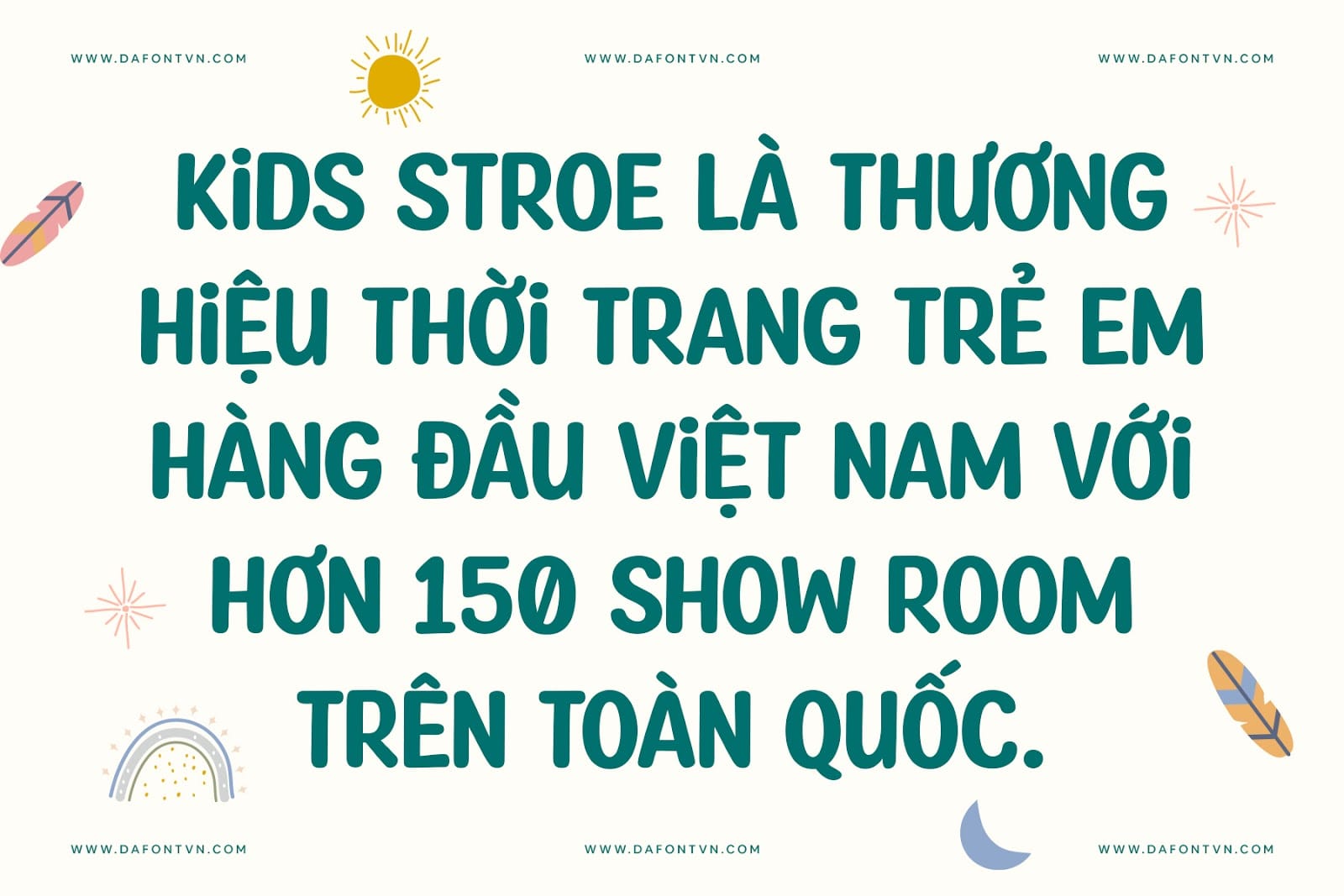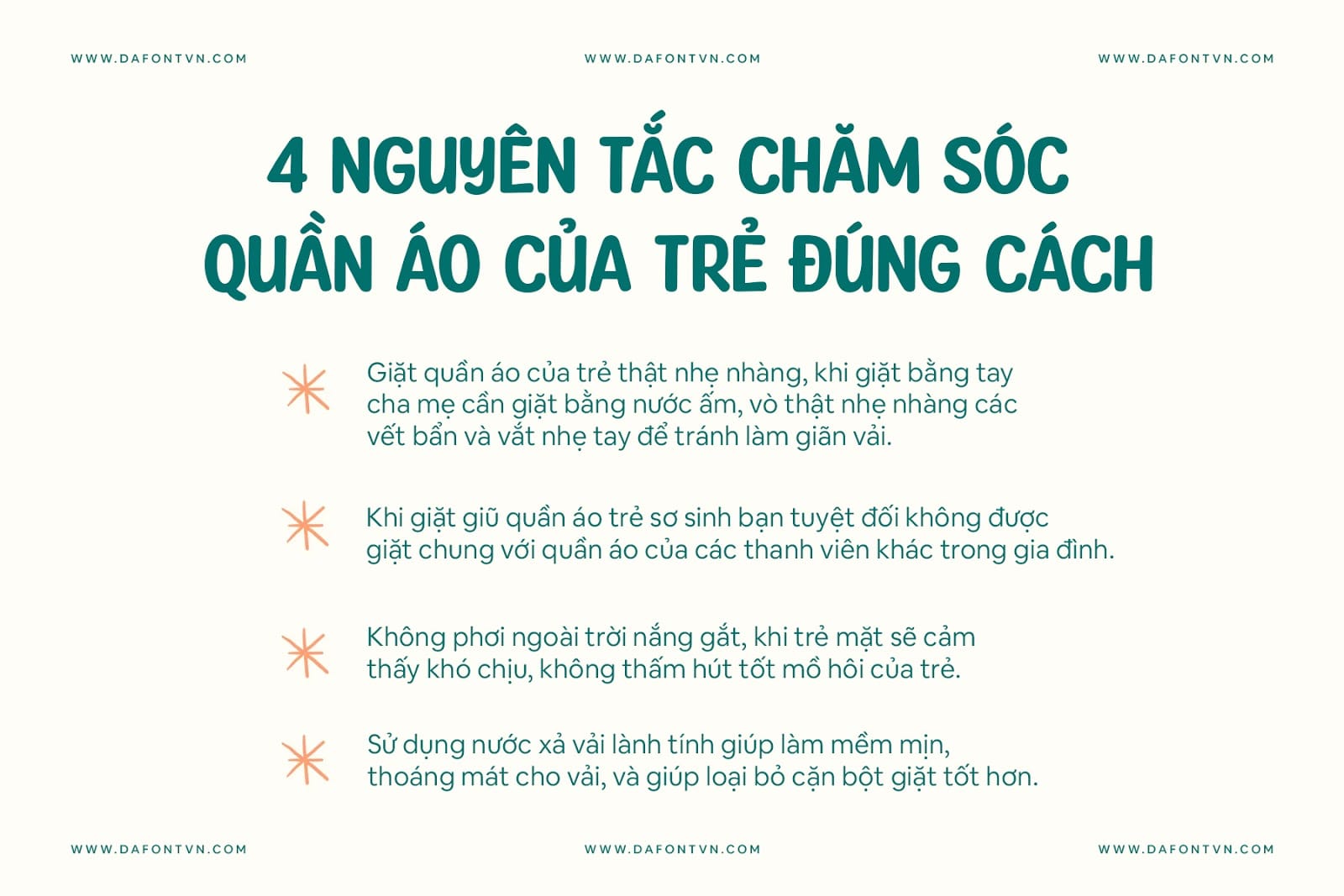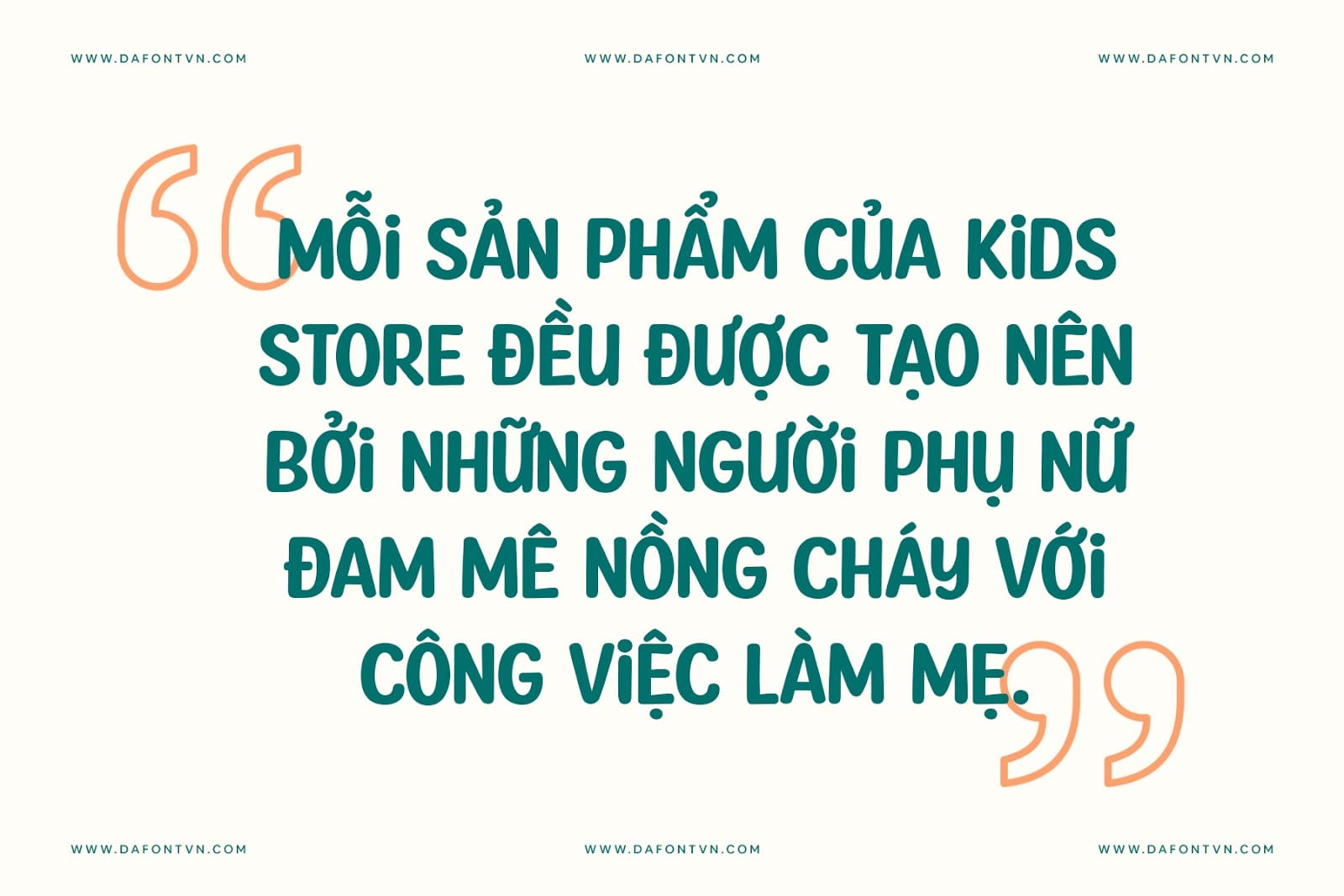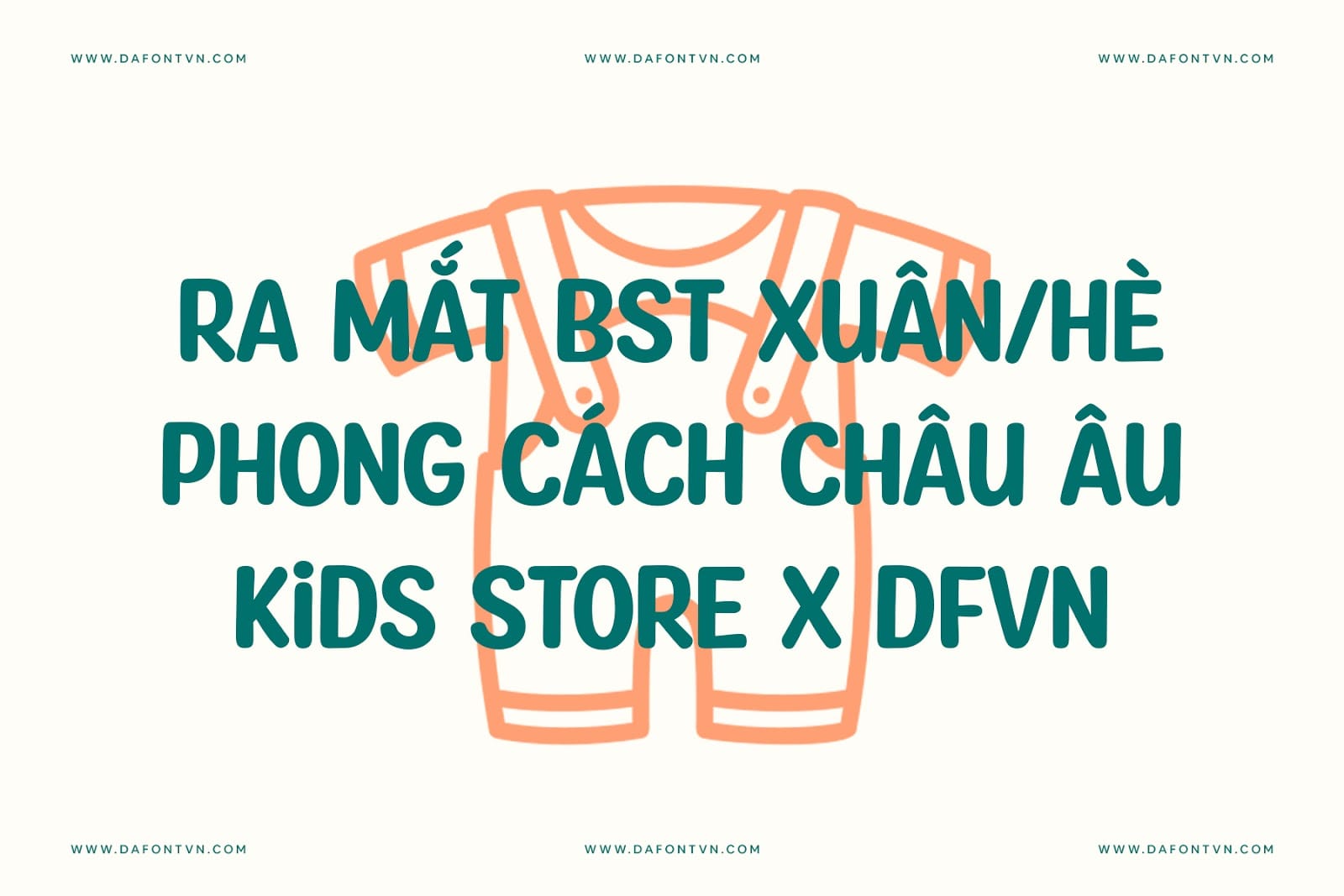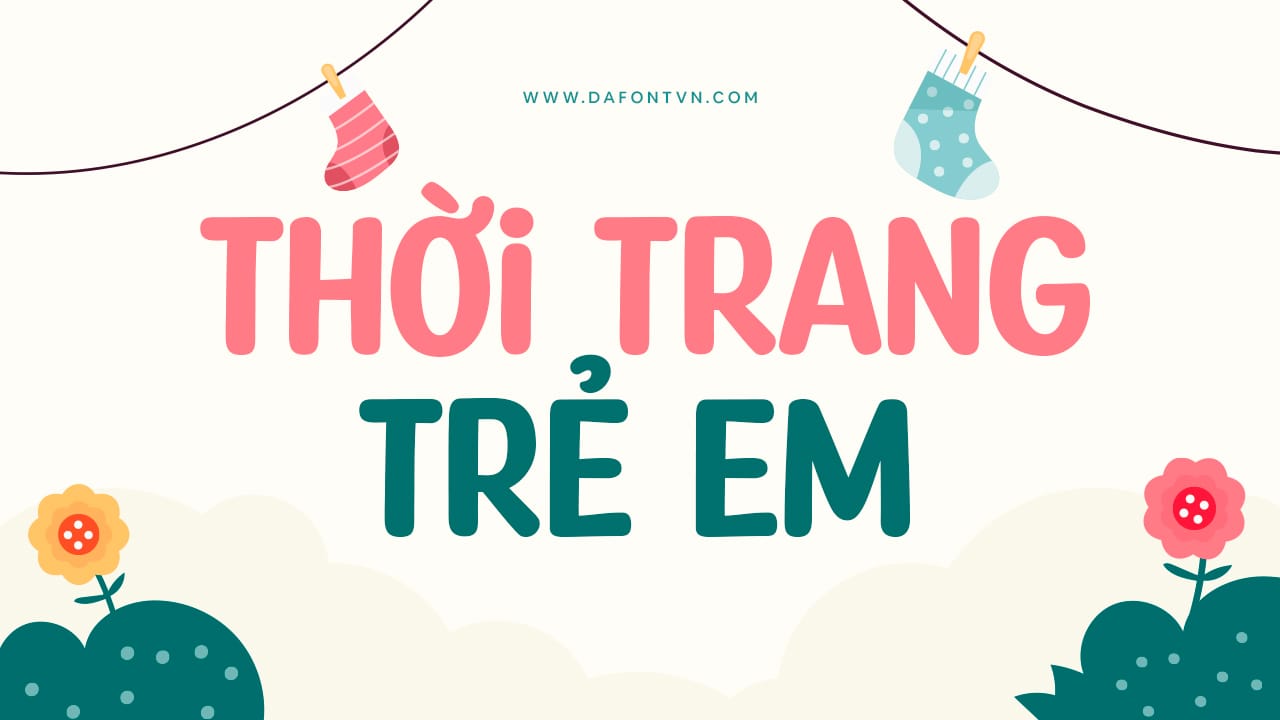
Lucky Skirt là một phông chữ hiển thị độc đáo, vui nhộn và vui tươi. Các ký tự được thiết kế tròn trịa và mập mạp của nó làm cho kiểu chữ này trở thành một kiểu chữ cực kỳ linh hoạt.Các ký tự đều in hoa, duy nhất chữ i được thiết kế kiểu thường, font việt hóa đầy đủ, ngoài ra được căn chỉnh lại các dấu để hiển thị tốt hơn. Lucky Skirt hoàn hảo cho nhiều thiết kế như tiêu đề, trích dẫn, logo, thiệp mời, trang trí, sản phẩm…